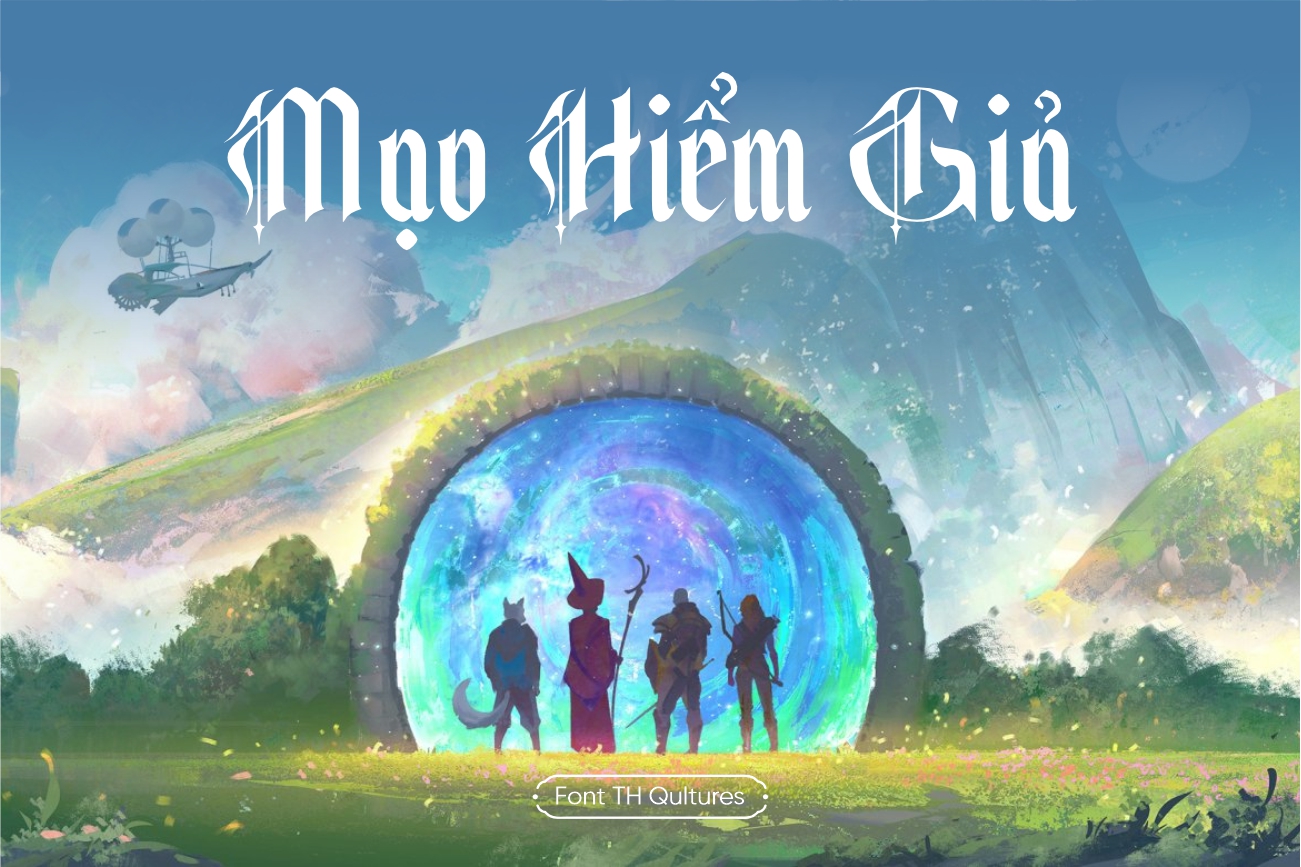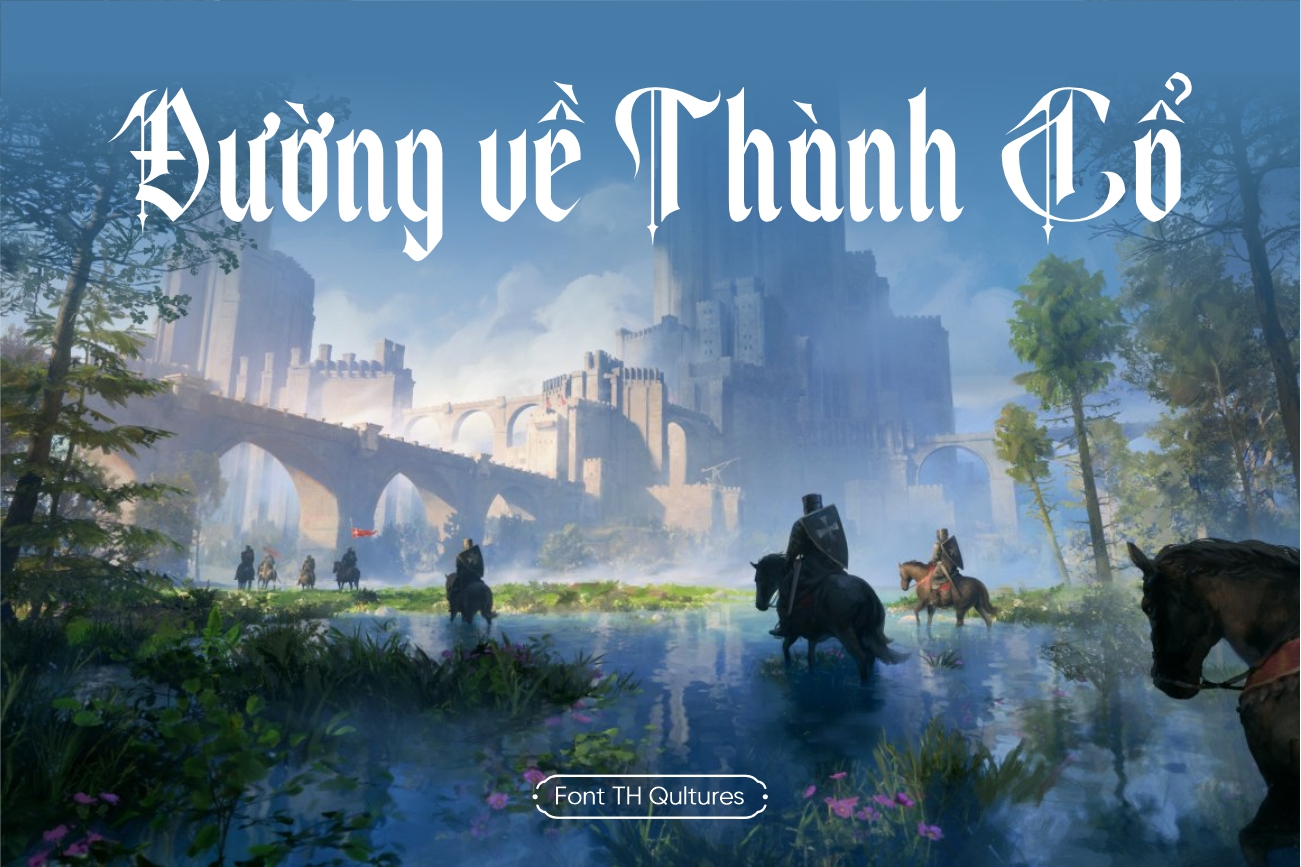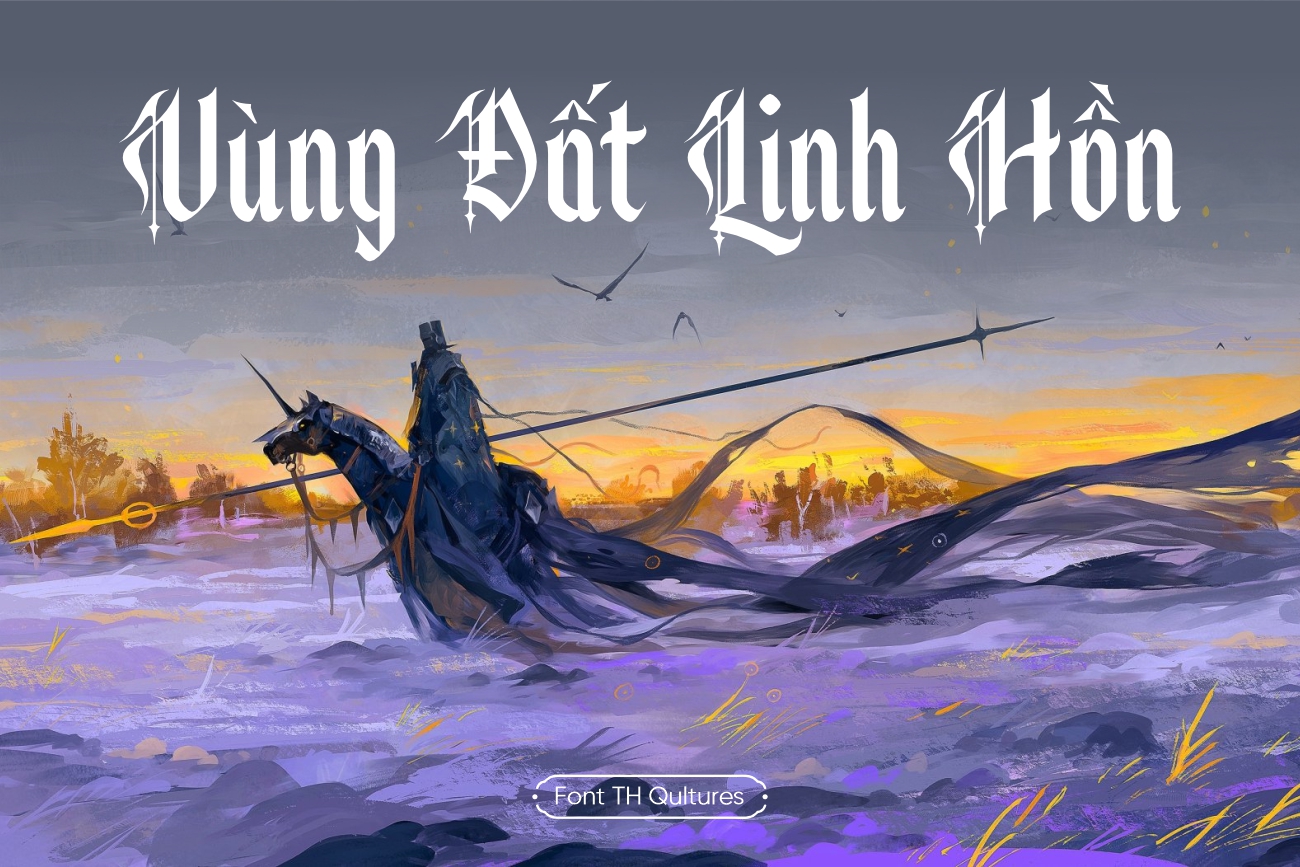
TH Qultures – Font Chữ Gothic Cổ Điển Cho Tiêu Đề Game
Nếu bạn đang tìm kiếm sự phá cách đầy mạnh mẽ cho các thiết kế mang hơi hướng huyền bí, TH Qultures chính là sự lựa chọn không thể bỏ qua. Đây là một mẫu font chữ Gothic (Blackletter) sở hữu những đường nét sắc sảo, dứt khoát và đầy uy quyền. Không giống như những font chữ mềm mại thông thường, TH Qultures mang trong mình linh hồn của những câu chuyện thần thoại phương Tây, tái hiện lại vẻ đẹp gai góc của những bản thảo viết tay từ thời trung cổ nhưng được cách điệu để phù hợp với thị giác hiện đại.
Với đặc tính hiển thị mạnh mẽ và ấn tượng, TH Qultures được đánh giá là một font chữ tiêu đề game xuất sắc, đặc biệt phù hợp cho các dòng game nhập vai (RPG), chiến thuật hay phiêu lưu mạo hiểm bối cảnh Châu Âu cổ xưa. Như các bạn thấy trong các bản demo như "Vùng Đất Linh Hồn" hay "Mạo Hiểm Giả", font chữ này tạo ra cảm giác sử thi, hào hùng ngay lập tức cho người xem. Ngoài ra, sự kết hợp giữa các nét xước và chân chữ gãy gọn cũng biến TH Qultures trở thành ứng cử viên sáng giá cho các thiết kế logo rock band, bìa sách kinh dị, hoặc làm font chữ cho các tiệm xăm nghệ thuật (Tattoo) muốn thể hiện cá tính riêng biệt.
Về nguồn gốc, bộ font này có tên gốc là Qultures, một sản phẩm sáng tạo độc đáo được thiết kế bởi tác giả Rinto Dwi Nugroho thuộc Almeera Studio. Nhận thấy sức hút của dòng font chữ cổ điển này tại Việt Nam, Team TH đã tiến hành Việt hóa trọn bộ, chăm chút kỹ lưỡng từng dấu câu để đảm bảo các ký tự tiếng Việt hiển thị mượt mà và đồng bộ nhất với phong cách gốc. Nhờ bản Việt hóa từ Team TH, các Designer giờ đây có thể thoải mái thả hồn vào các poster phim, banner sự kiện hay ấn phẩm quảng cáo đậm chất nghệ thuật mà không còn lo ngại về lỗi font.